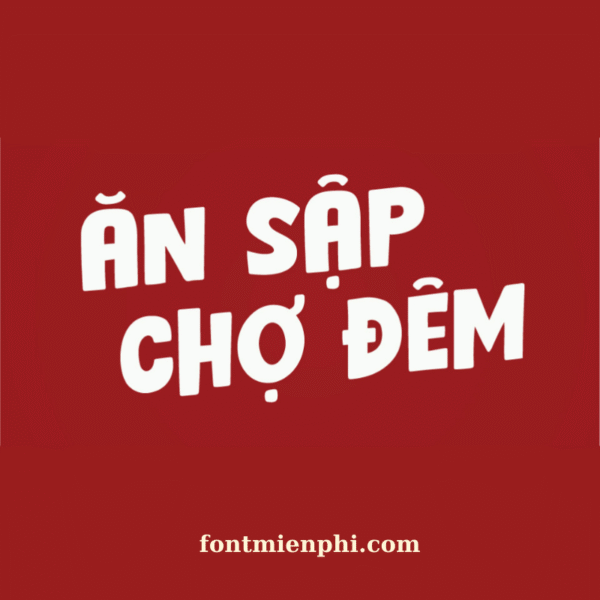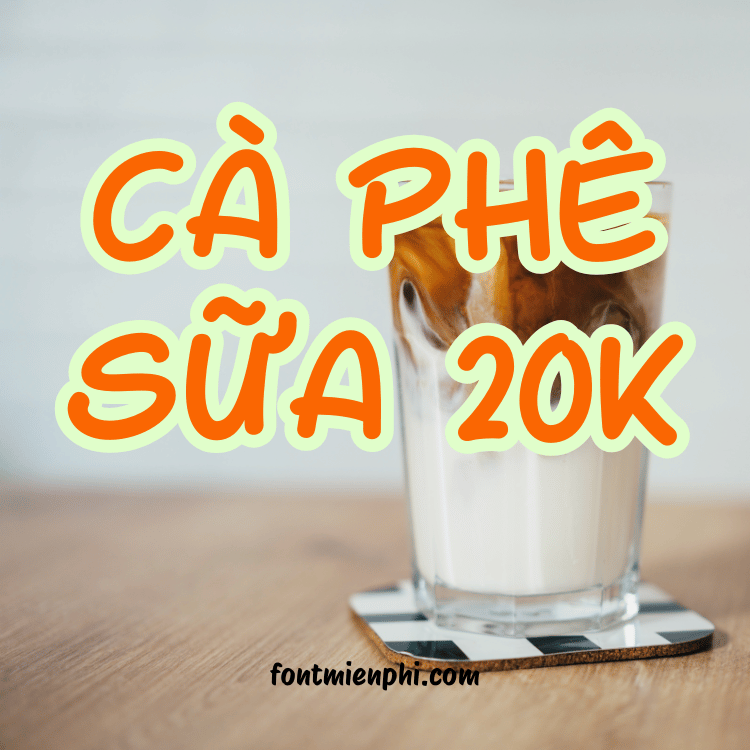
Font Việt hóa FMP Wine Season, Font VIP
Giới thiệu về Font Việt hóa FMP Wine Season, Font VIP
Trong thế giới đồ họa hiện đại, việc tìm kiếm một bộ Font Miễn Phí chất lượng cao là ưu tiên hàng đầu của các nhà thiết kế. Font Việt hóa FMP Wine Season, Font VIP nổi lên như một lựa chọn hoàn hảo cho những dự án đòi hỏi sự tinh tế và sang trọng. Đây là bộ phông chữ được tinh chỉnh kỹ lưỡng, hỗ trợ đầy đủ tiếng Việt giúp người dùng dễ dàng ứng dụng vào các tác phẩm nghệ thuật mà không lo lỗi hiển thị. Với phong cách thanh lịch, bộ font này đặc biệt phù hợp cho các chủ đề về ẩm thực, sự kiện và thương hiệu cao cấp.
Đặc điểm nổi bật của Font Việt hóa FMP Wine Season, Font VIP
Thiết kế tinh tế và chuyên nghiệp
Font Việt hóa FMP Wine Season, Font VIP sở hữu những đường nét thanh thoát, mang hơi hướng cổ điển nhưng vẫn giữ được nét hiện đại cần thiết. Từng ký tự được chăm chút tỉ mỉ, tạo nên sự cân đối tuyệt vời cho các tiêu đề lớn hay các đoạn văn bản ngắn. Sự độc đáo của bộ font này nằm ở khả năng truyền tải cảm xúc mạnh mẽ, giúp người xem cảm nhận được sự chuyên nghiệp và đẳng cấp của thương hiệu ngay từ cái nhìn đầu tiên.
Khả năng ứng dụng linh hoạt
Dù bạn đang thiết kế menu nhà hàng, thiệp mời đám cưới hay bao bì sản phẩm, Font Việt hóa FMP Wine Season, Font VIP đều đáp ứng tốt các tiêu chuẩn khắt khe nhất. Bộ font này không chỉ đẹp trên màn hình kỹ thuật số mà còn hiển thị sắc nét khi in ấn thực tế. Đây chính là công cụ đắc lực giúp học sinh, sinh viên và các nhà thiết kế trẻ nâng tầm tư duy sáng tạo trong các bài tập trình bày hoặc dự án cá nhân.
Kết luận về bộ Font Việt hóa FMP Wine Season, Font VIP